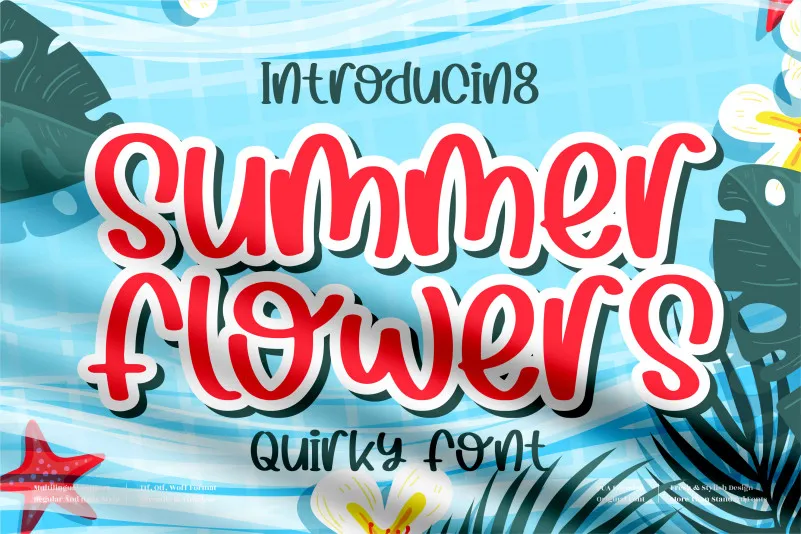
Summer Flowers Font – Fonte Grátis
Summer Flowers Font
A “Summer Flowers Font” é uma opção única para aqueles que buscam imprimir personalidade em seus projetos. Inspirada na essência verão e na beleza das flores, essa fonte de escrita manuscrita apresenta um charme peculiar ideal para inúmeros usos, como logomarcas, projetos de marca, designs de mobília, embalagens de produtos, tigelas de café, cartazes, sacolas de shopping, camisetas, capas de livros e até mesmo selos. Ela também atende a uma variedade de outros projetos, como cartões de nome, cartões de convite, cartões de felicitações, etiquetas e até mesmo trabalhos fotográficos ou gráficos. Se você está procurando por uma fonte que adiciona um toque especial e quirk ao seu projeto, a “Summer Flowers Font” é perfeita para esse papel. Assim como o verão e suas cores vibrantes e flores coloridas, essa fonte traz vida, alegria e personalidade aos seus trabalhos de design.